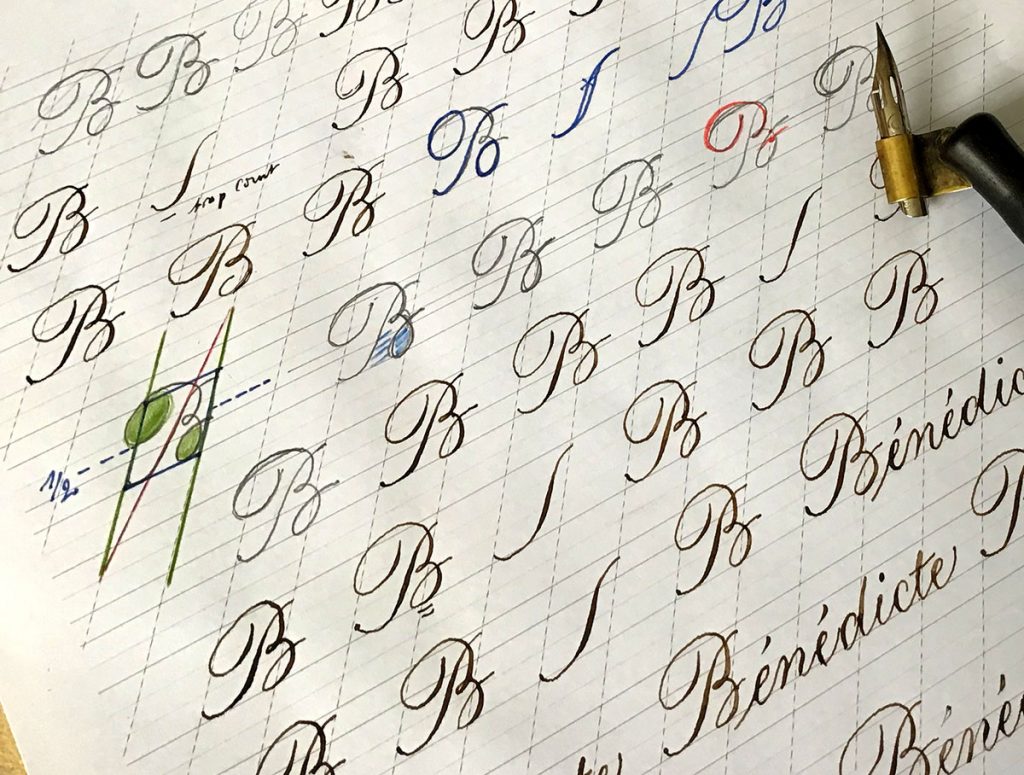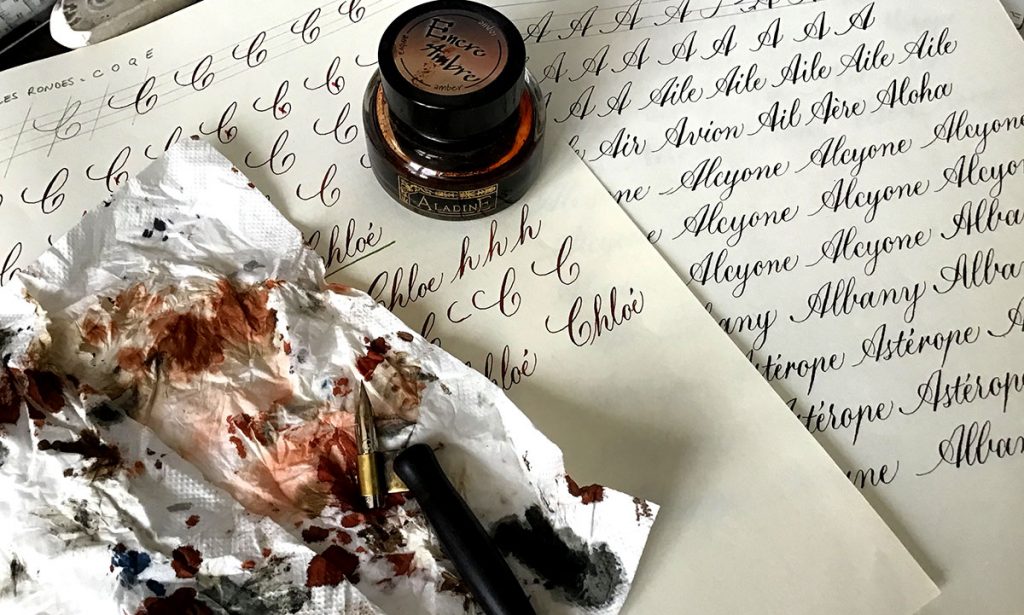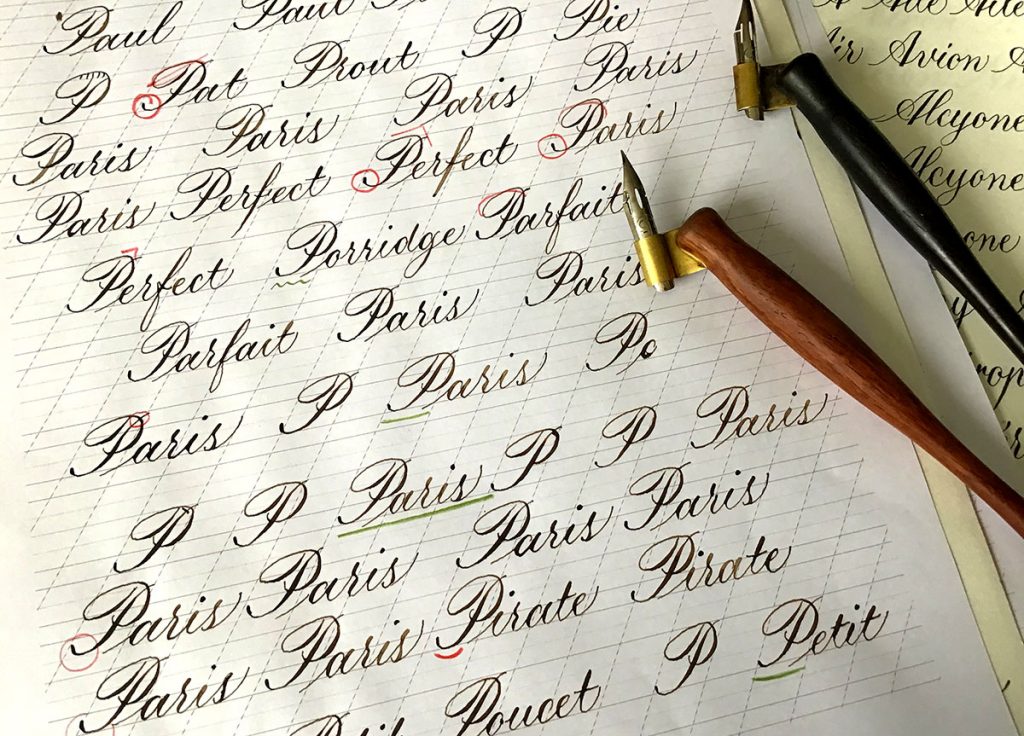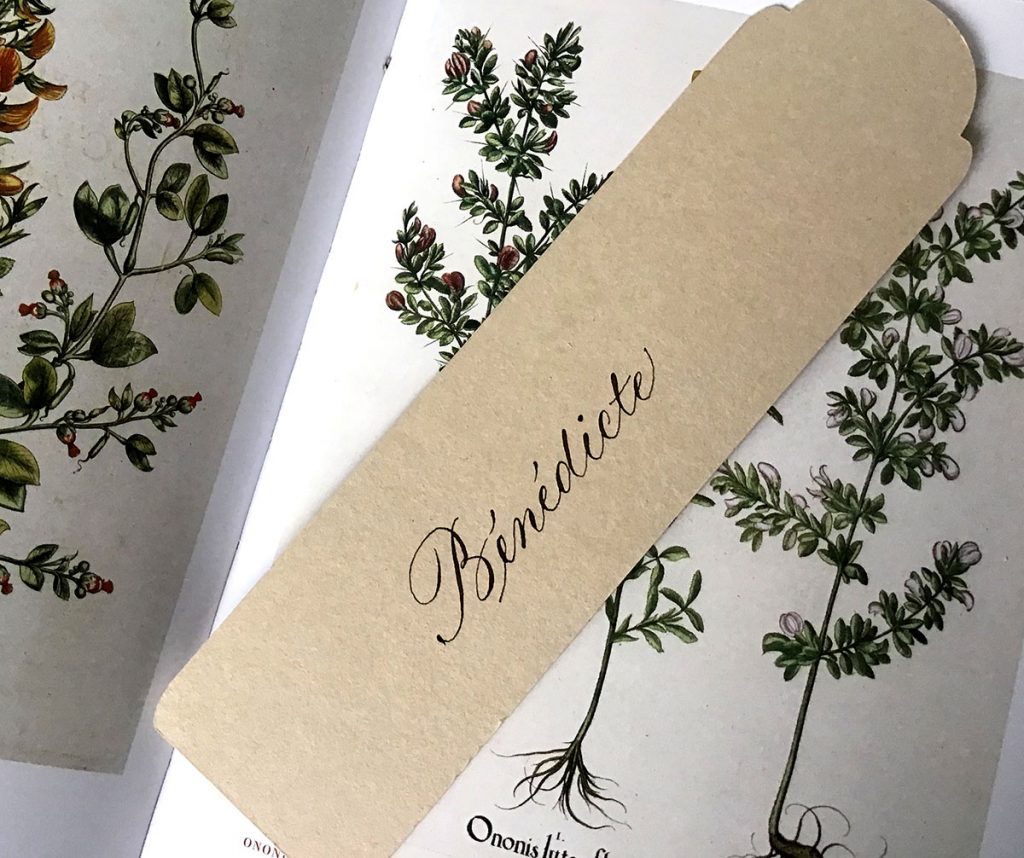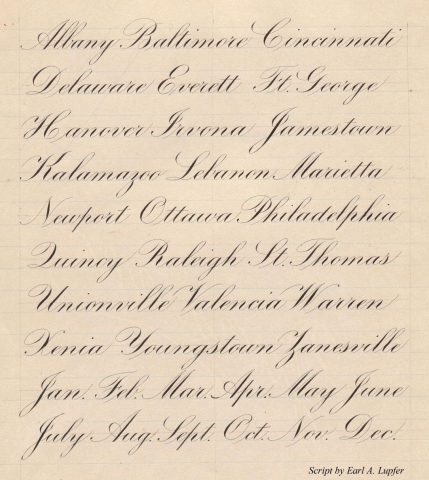
La rentrée de septembre marque toujours une période propice à la reprise des écritures. L’an dernier, je m’étais attelée à la Spencerian, l’année d’avant à la Chancelière : cette année c’est sur l’Anglaise que je jette mon dévolu, avec la ferme intention d’y consacrer quelques semaines d’entraînement régulier et soutenu. J’ai commencé l’anglaise en 2015 et fin 2017 j’avais une main plutôt honorable, quoiqu’imparfaite. J’aimerais maintenant la pousser au niveau supérieur : plus d’élégance, plus de peps, plus de froufrous (arabesques), plus de claaaassse, quôa !
Ré-apprendre l’anglaise après des mois sans pratiquer
Je n’ai pas touché une plume pointue depuis des mois, et encore moins fait de l’anglaise : la reprise a été des plus frustantes, évidemment. La calligraphie, ce n’est pas comme la bicyclette : il ne suffit pas de reprendre sa plume pour repartir comme en 40. Lorsque j’ai vu que même Suzanne Cunningham – qui est un peu une déesse de la Copperplate – faisait des pages d’entraînement pour se remettre en main, j’ai décidé humblement de reprendre les bases, sans froufrou ni chichi.
Réarmée d’une plume neuve, me voici repartie au pays des ovales, des pleins et des déliés, avec un focus particulier sur les majuscules que je n’avais jamais vraiment travaillé en fait.
Pour reprendre ces basiques j’utilise une planche toute simple de Lupfer, car elle produit les majuscules dans leur forme la plus basique et montre bien l’espacement, les formes et la pente.
J’ai aussi consulté le manuel (gratuit !) de Dr Joseph M. Vitolo, Script in the Copperplate Style©, disponible sur le site IAMPETH. Ce manuel de 87 pages est très bien fait et comporte de nombreux liens vers des vidéos.
Ma façon de pratiquer
Suite aux stages assez intensifs avec Yves Leterme, j’ai évolué dans ma façon d’apprendre et de pratiquer. En particulier, mais c’est peut-être aussi le fruit des années, je suis beaucoup plus attentive aux formes et aux proportions. Lors de mes début en calligraphie, j’étais un peu en mode “je m’en fous, je fais ce qui me plaît”. Bon, bah… a force de côtoyer des pointures et d’avoir aiguisé mon oeil (ça se dit ?), je suis devenue beaucoup plus exigeante, plus humble aussi. Lorsque je reprends une écriture après des mois sans avoir pratiqué, je reprends donc la base.
C’est un peu comme la danseuse qui s’exerce sur une pirouette, comme le musicien qui refait ses gammes. Même Nadal, quand il reprend l’entraînement, va enchaîner 40 volées et 50 services pour se remettre dans le bain. Voilà en gros l’état d’esprit.
“Ah oui, mais alors tu vas te manger des pages d’écritures”, me demanderez-vous ? Il y a un peu de ça, en effet, pour retrouver le geste, les sensations et parvenir à la meilleure exécution possible. Tout ça c’est plein de promesses, et en attendant, il faut s’armer de persévérance, et d’un bon stylo rouge.
Mes pages d’entraînement
Les réseaux sociaux et les blogs en général n’affichent que du beau : je me permets de vous montrer du “pas abouti”. La vérité c’est que derrière des petites vidéos/photos sublimes se cachent des centaines d’heures de pratique. Donc… pour ne pas décourager les novices ou ceux qui souhaitent atteindre un très bon niveau, je vous livre un vrai bout du chemin (en espérant que d’ici quelques semaines je pourrais vous montrer du “sublime” sinon j’aurais vraiment l’air tarte !).
Pour finir la séance, un petit marque page qui ne demande qu’à être enjolivé :